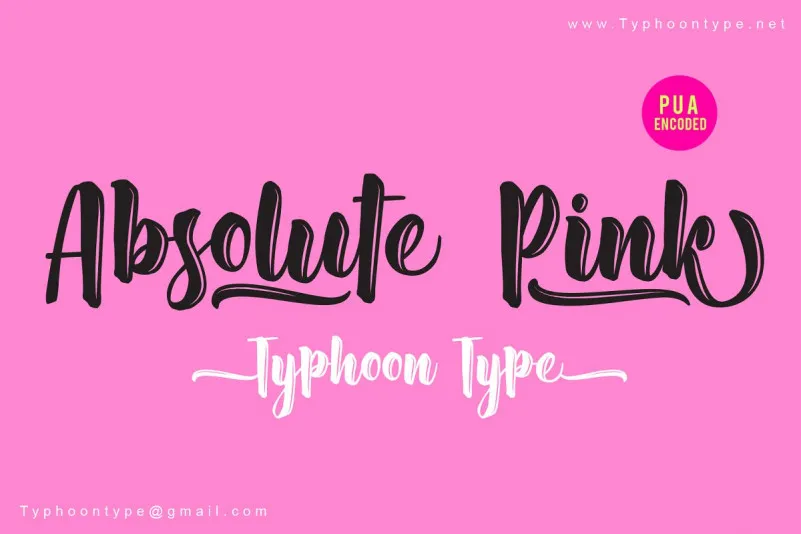
Descubra absoluta perfeição com a Fonte Absoluta Cor-de-Rosa Script. Ideal para designers que desejam adicionar uma nota de elegância e originalidade aos seus projetos, a Absoluta Pink Script Font é uma escolha perfeita. Esta fonte Vintage Script Brush tem um estilo de traço com pintura à mão, oferecendo inúmeras características de tipo opentype úteis para o seu trabalho. Através de sua versão script, pode-se criar elementos elegantes e únicos, seja em design gráfico, arte elementar, estilização para casamentos ou eventos, criação de t-shirts, desenvolvimento de logotipos, criação de selos ou qualquer projeto que exigir um toque especial. Sem dúvidas, a Absoluta Pink Script Font é uma fonte ideal para quem busca inspiração e criatividade em sua próxima peça de arte.